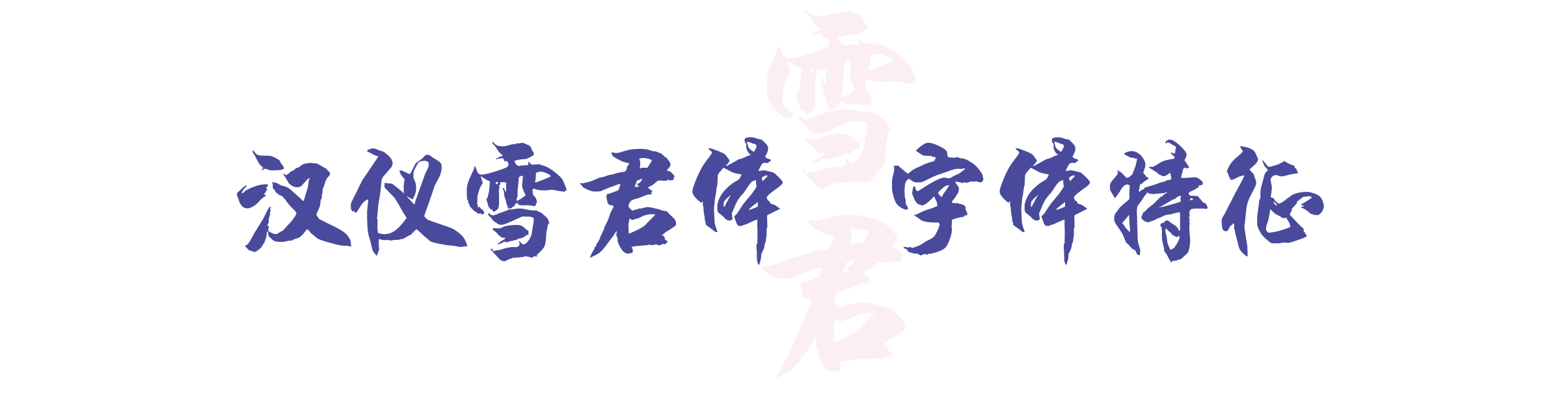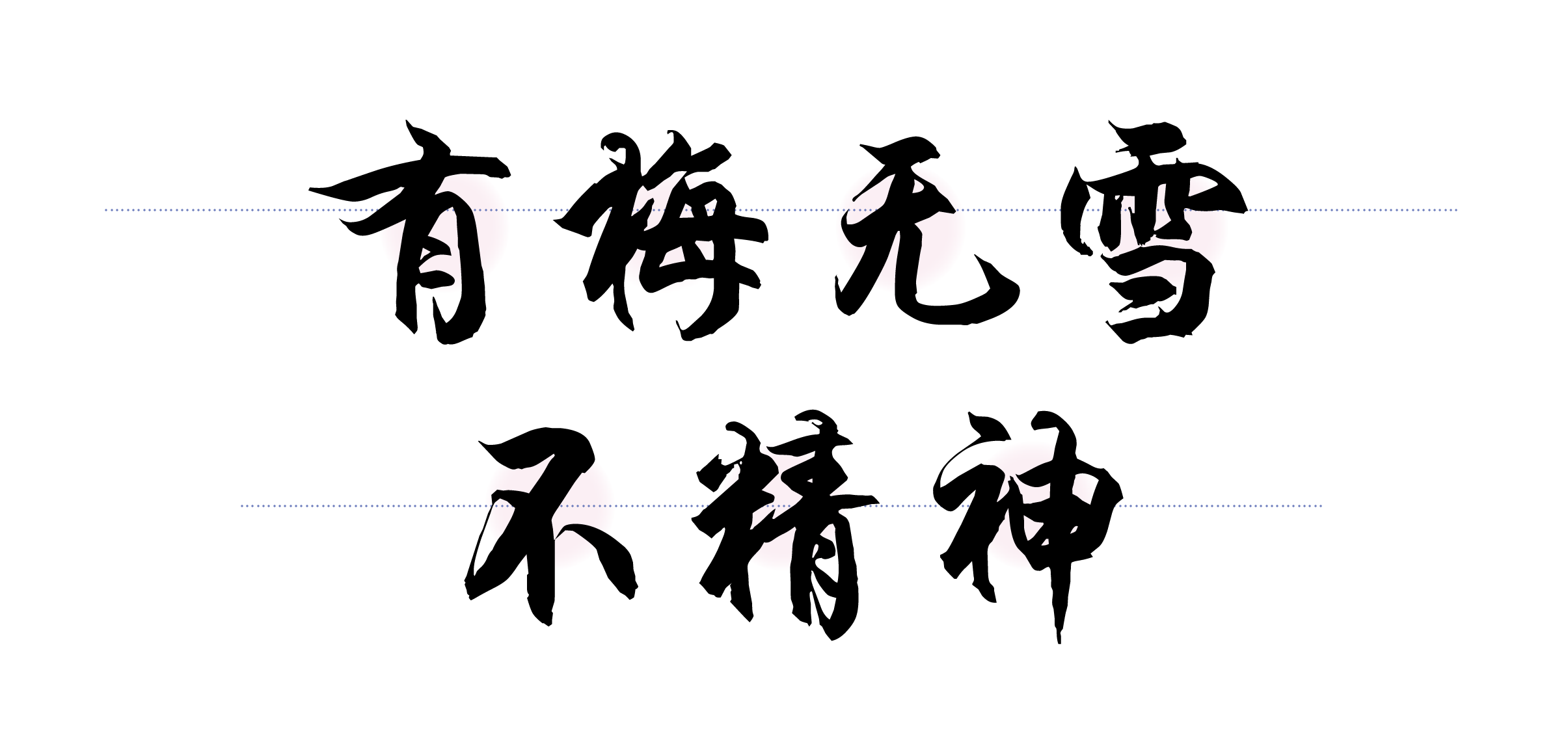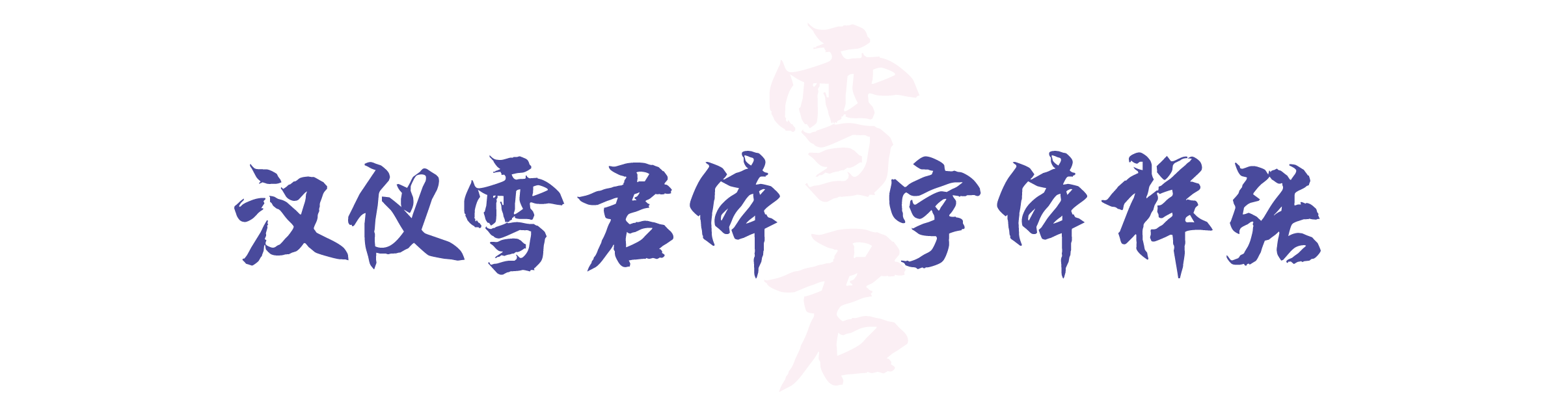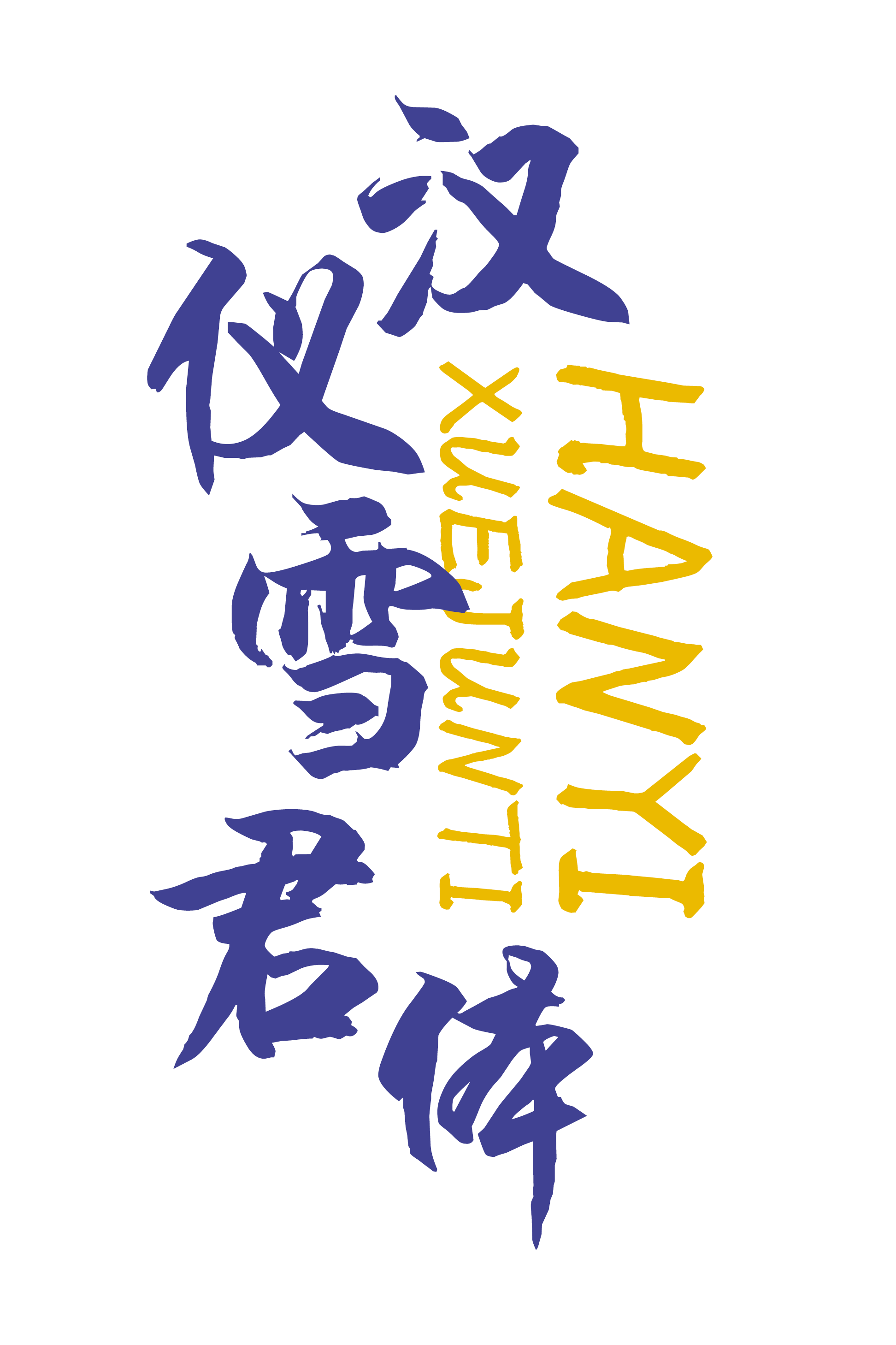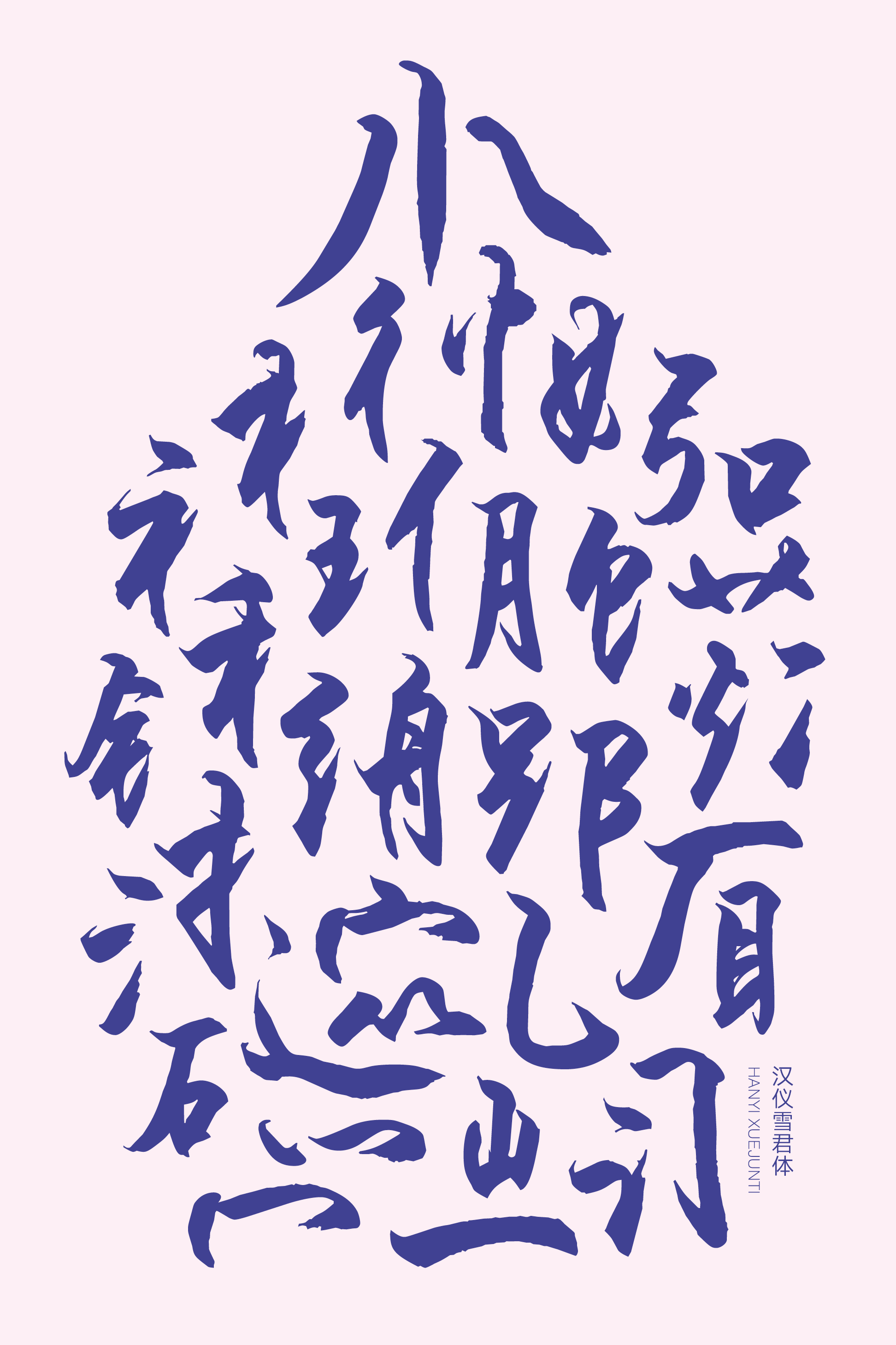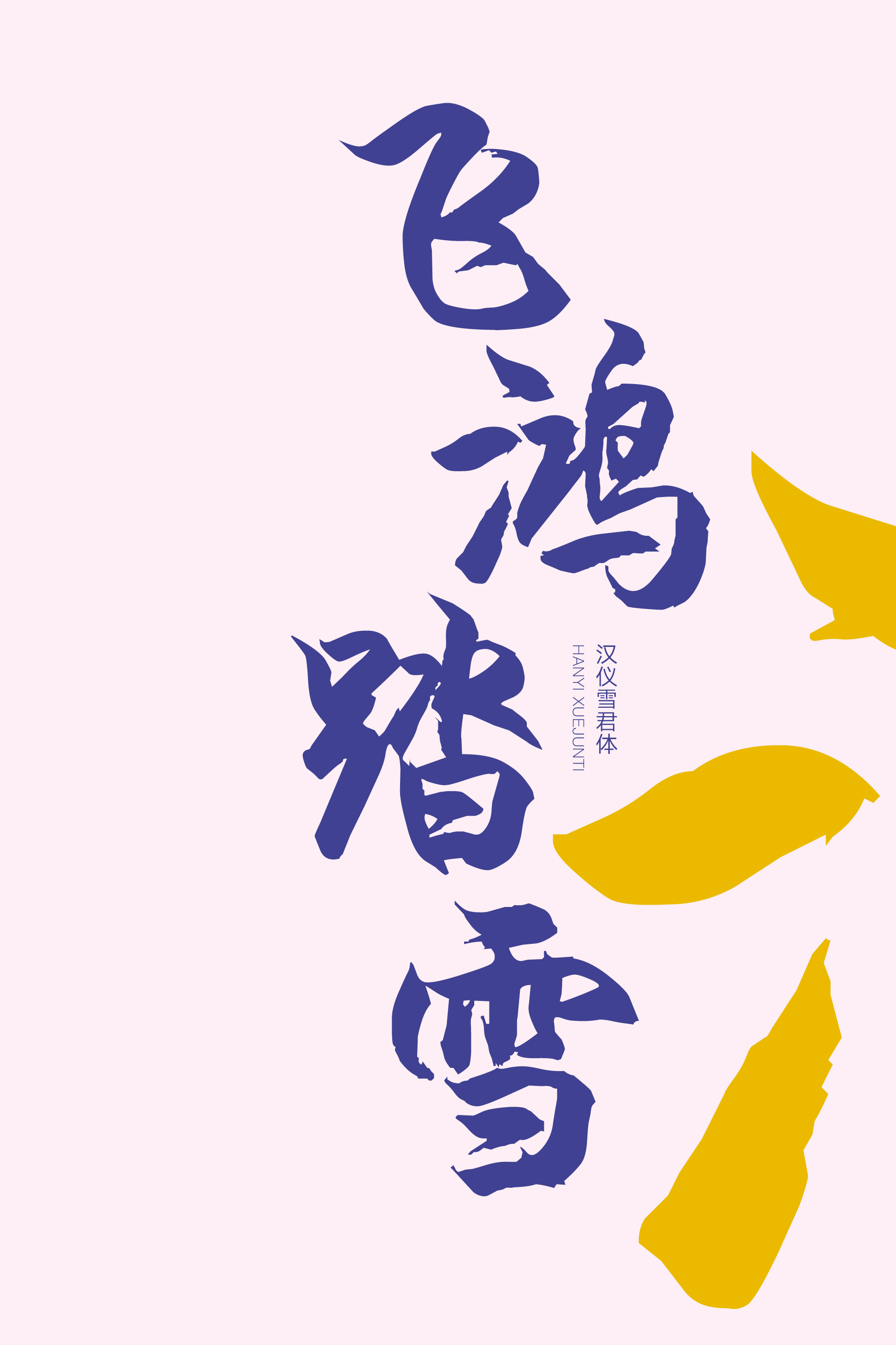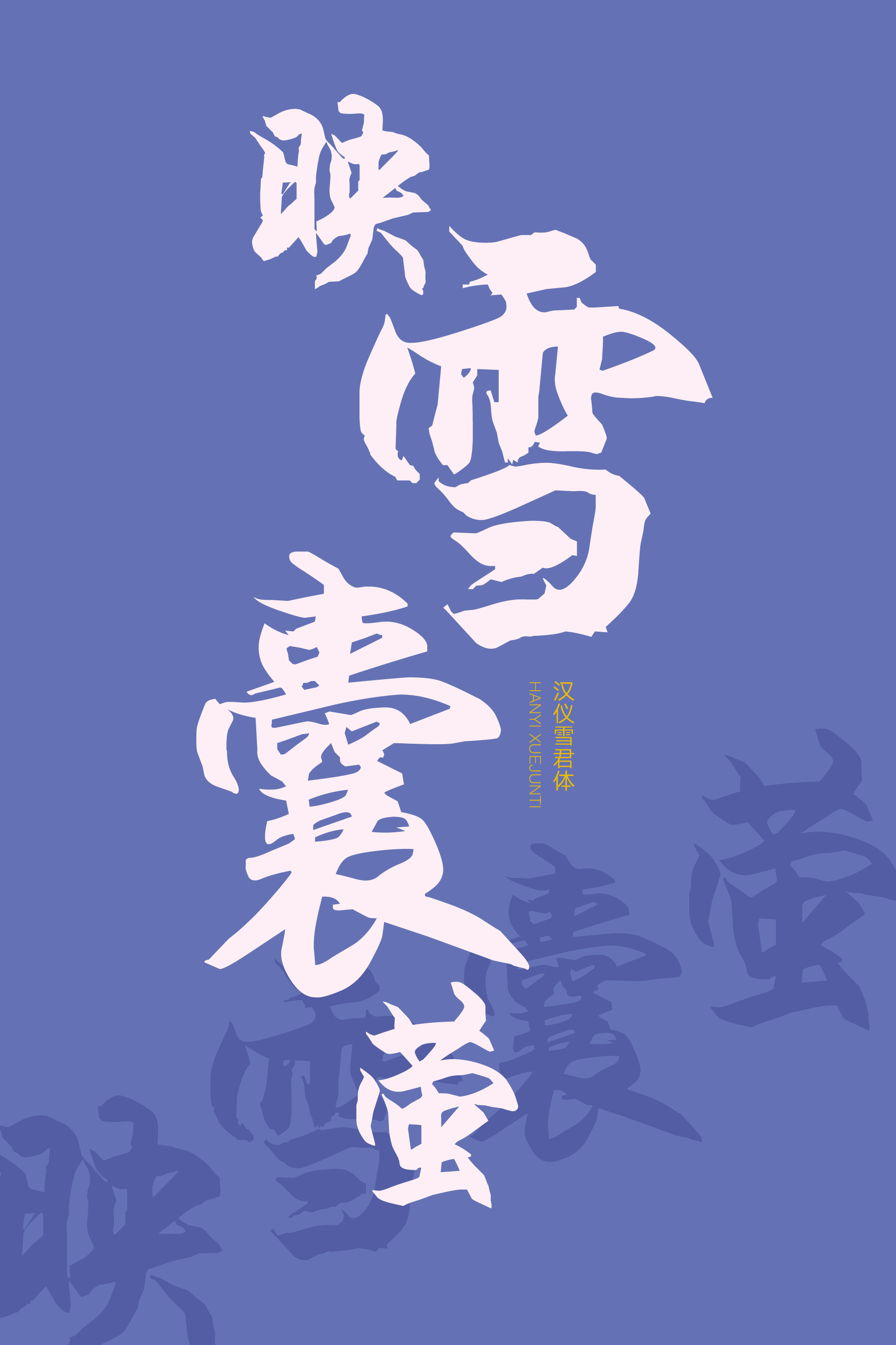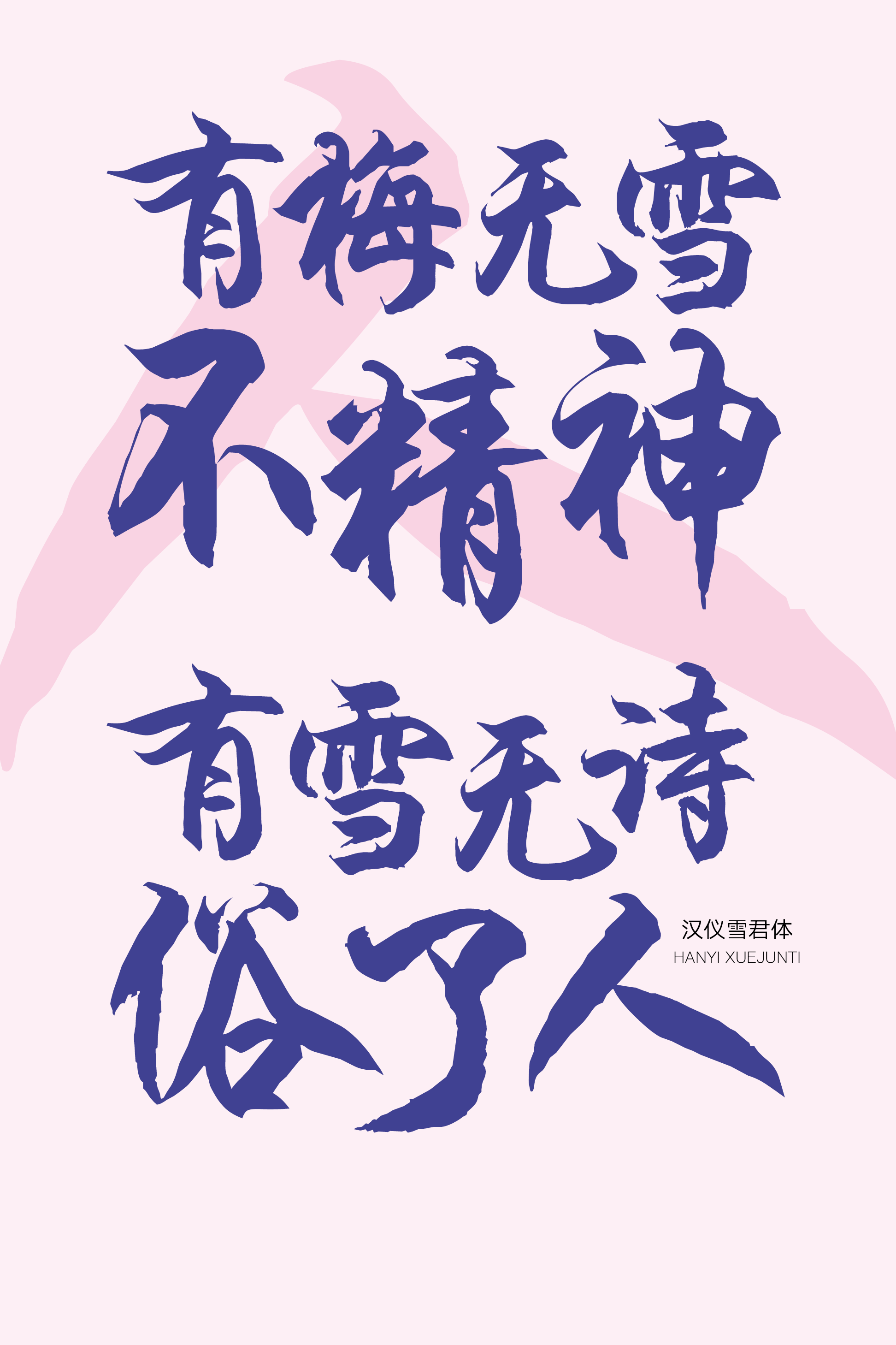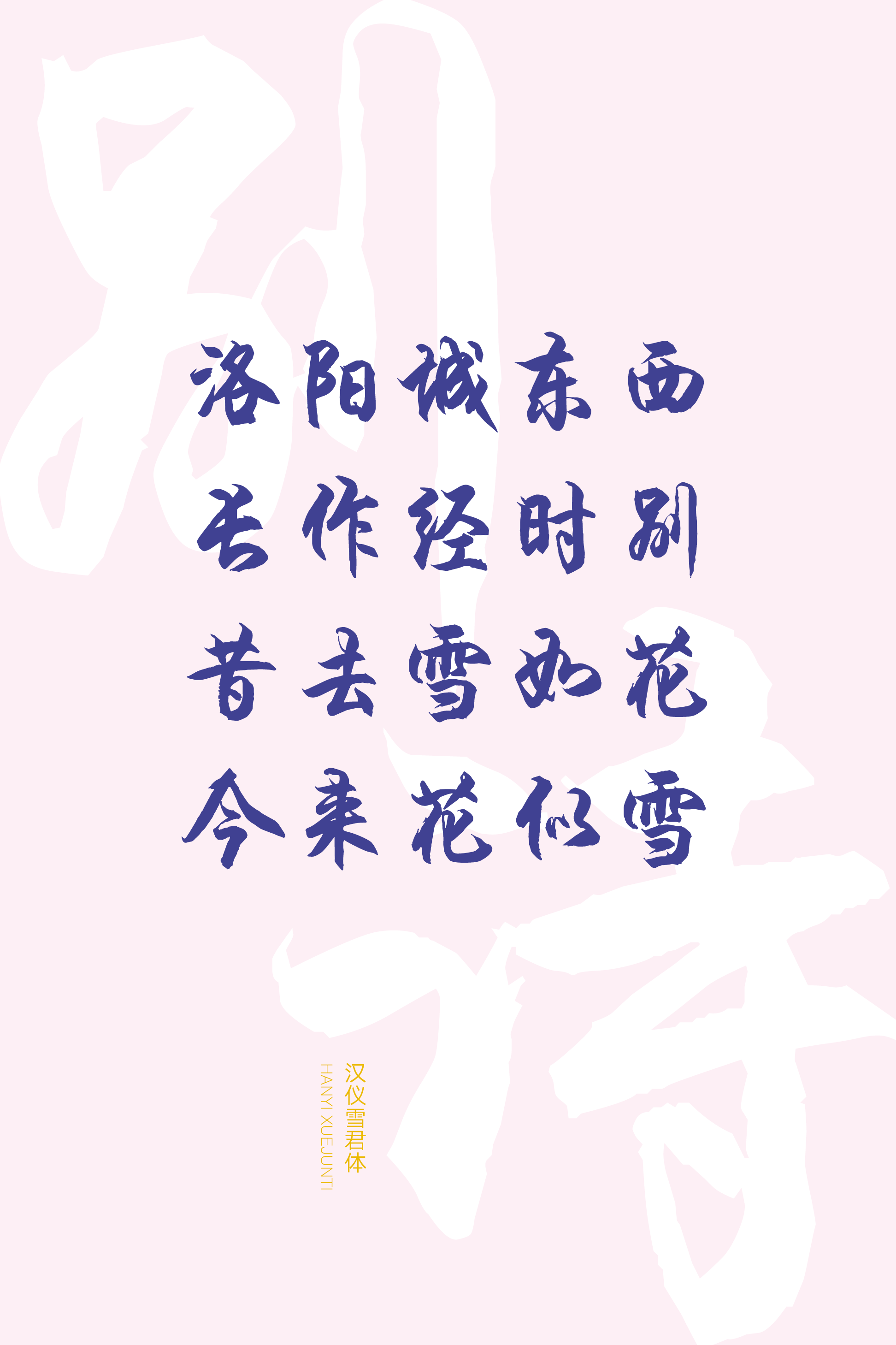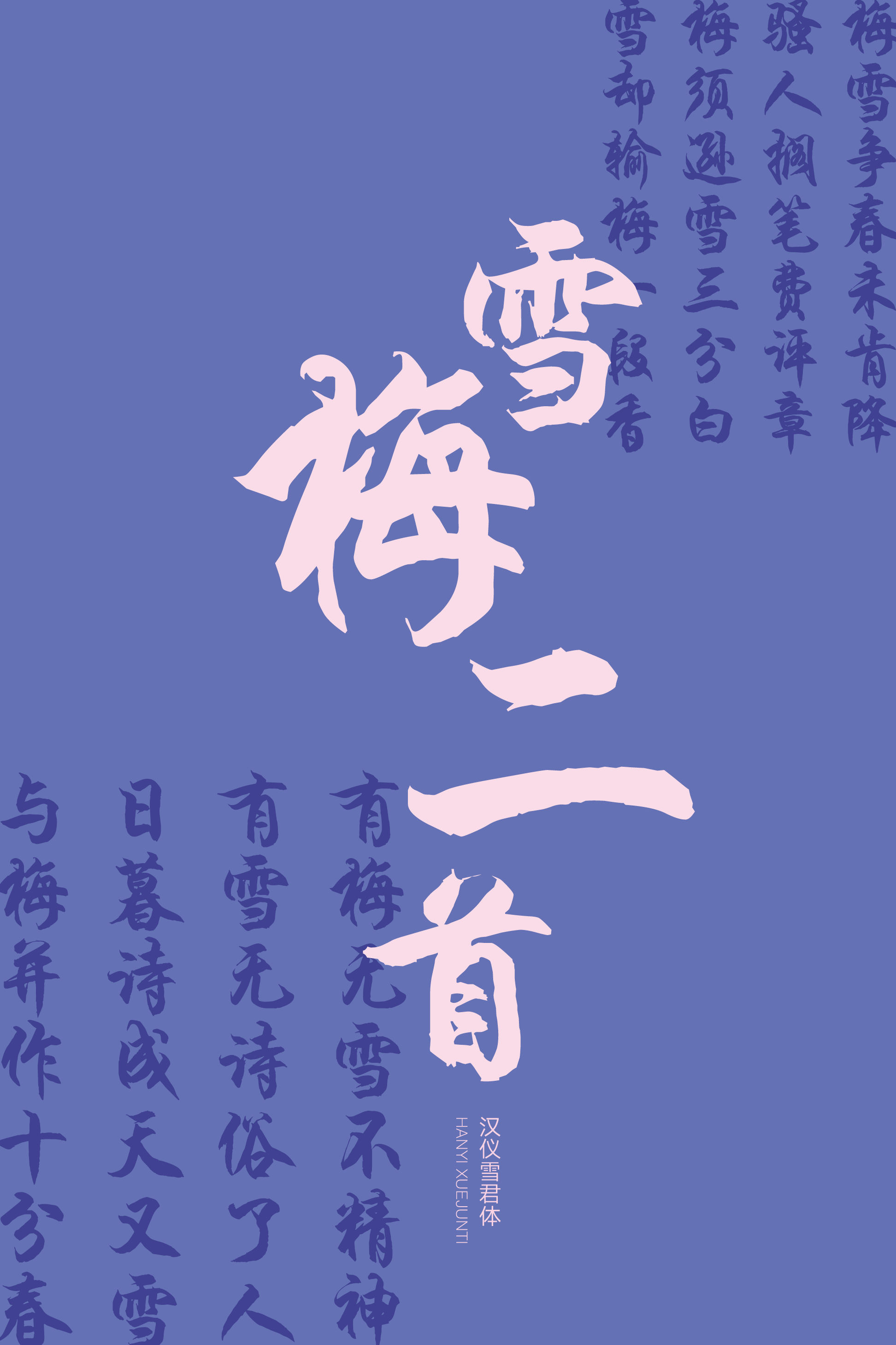
汉仪雪君体
汉仪雪君体,由著名书法家雪君于1998年至2000年间书写。这款书法标题字体刚柔并济,潇洒自如,笔画粗重,风格典雅大方、严肃工整。作为一款优质的早期电脑书法字库,汉仪雪君体以其实用性和艺术性被广泛应用于全国电视、书刊、报纸、杂志、网络、匾额、招牌等。
字形工整大方,重心偏高,中宫紧凑,精神气质挺拔。
用笔重墨,笔画绵厚而潇洒。